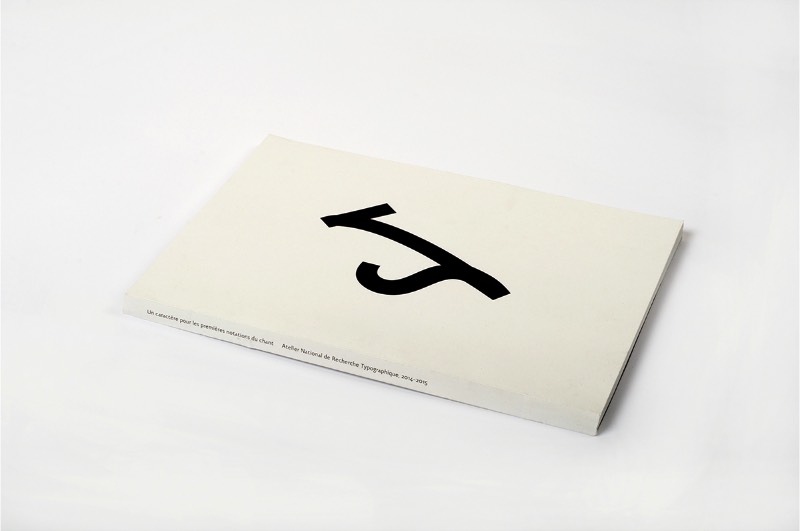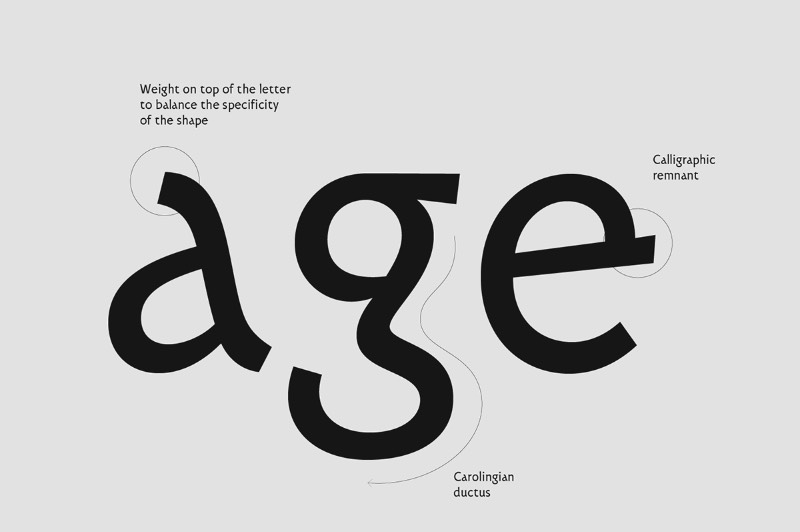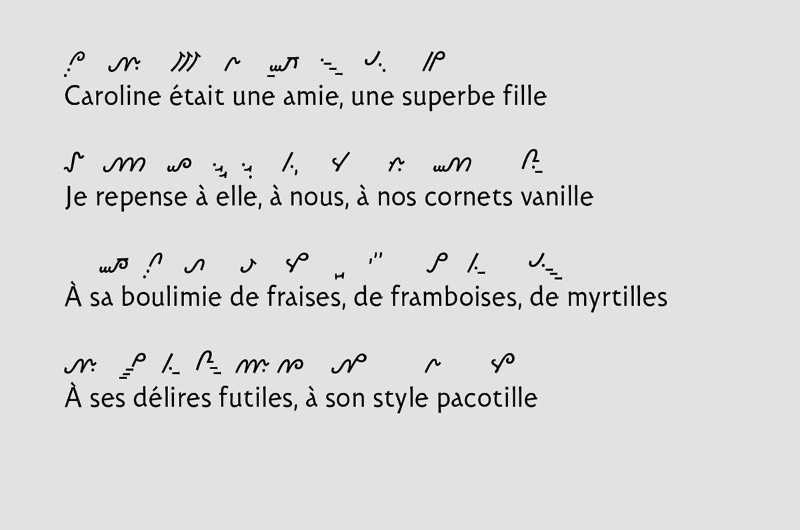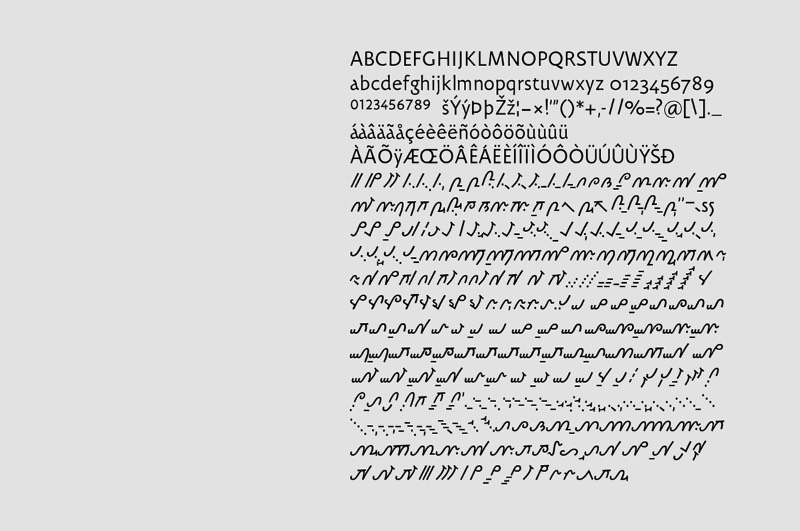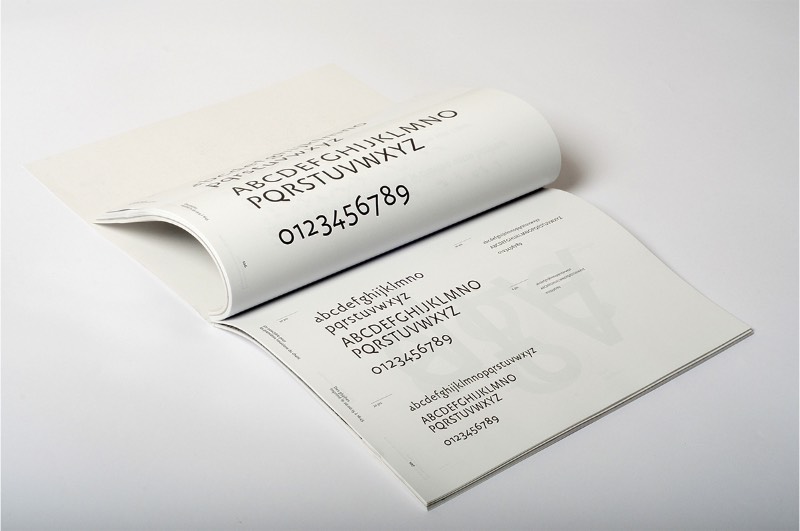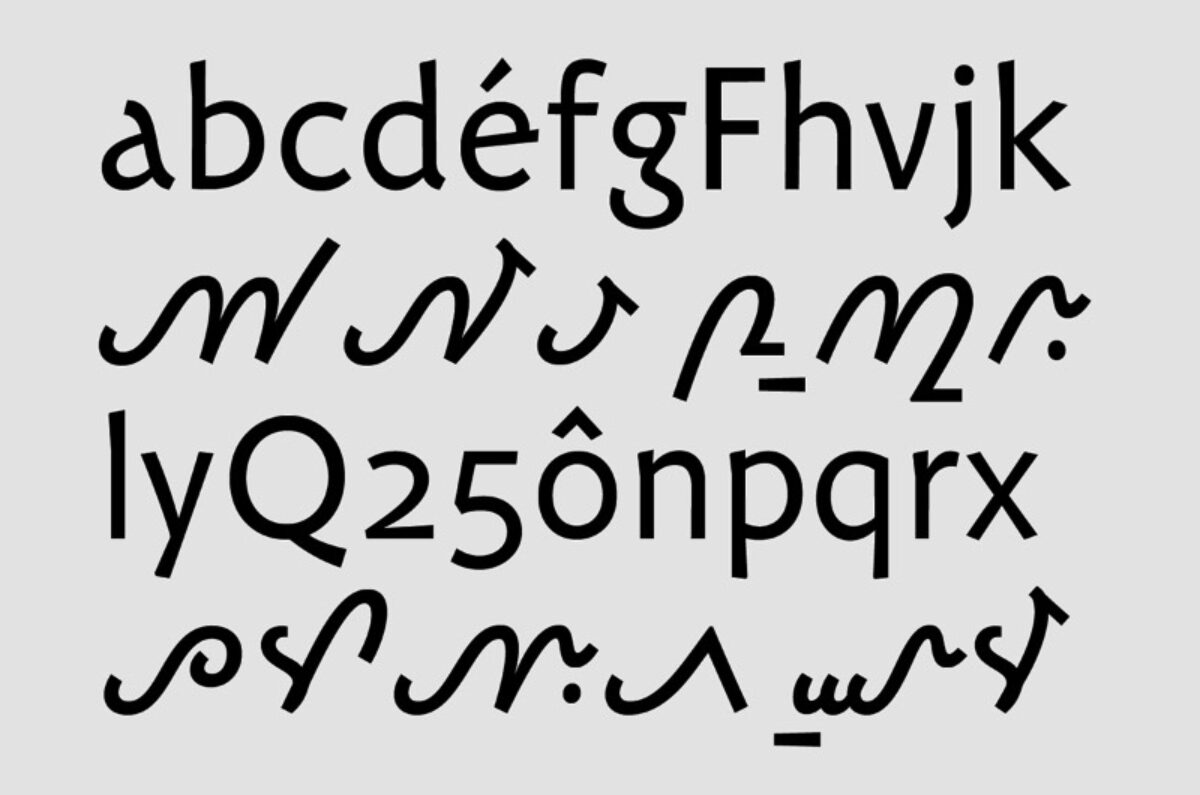
Carolinéale é uma fonte criada pelo estúdio Nouvelle Étiquette e inspirada em Escrituras Carolíngias
Foi com o surgimento das primeiras formas de se escrever notas musicais que chegou o fim de uma tradição secular de transmitir melodias através de um boca a boca. Isso tudo começou a acontecer a partir do século VIII e acabaram evoluindo para o sistema de notas musicais escritas que temos hoje em dia. Carolinéale é uma fonte criada pelo estúdio de design gráfico francês Nouvelle étiquette, que já apareceu aqui antes, e seu design foi inspirado por escrituras Carolíngias dessa época. Ou seja, essa família tipográfica é uma verdadeira viagem ao passado.
Como disse anteriormente, antes das notas musicais, as melodias eram transmitidas de outras formas. Alguns exemplos dessas formas primitivas de escrever música sobreviveram aos anos e podem ser observadas hoje em dia. Uma delas segue o estilo de escrituras de Messine e outra segue a de St. Gall. Hoje em dia, essas escrituras ainda servem como forma de interpretar cantos gregorianos da forma mais fiel possível.
A Carolinéale foi criada observando essas duas escrituras. Esses manuscritos servem de base para o projeto Gregorio, um software open-source que tem como objetivo a publicação de partituras usando o sistema de melodias carolíngio. Por culpa de todos esses detalhes, o processo de criação e design dessa fonte foi bem informal, seguindo desenhos de notas musicais primitivas e interpretação contemporânea de letras minúsculas de escrituras carolíngias. Dessa forma, o trabalho final é uma mistura de elementos do passado, sendo interpretados de uma forma moderna. Criando assim um fonte com o objetivo de ser legível, contemporânea e estável.
Carolinéale é uma fonte inspirada em Escrituras Carolíngias criada por Nouvelle étiquette